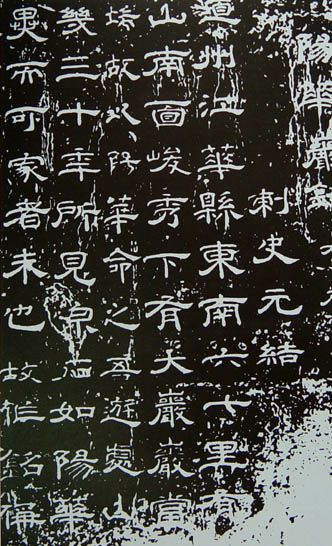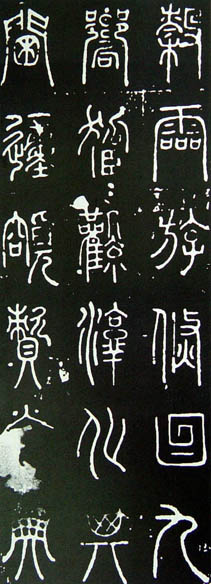
瞿令问简介
一作令闻,生平无考,或以为望出博陵(今河南蠡县),唐代宗时人。历道州江华县令,为元结道州刺史下属。工书,尤工杂体篆及八分。与元结友善,时元结为道州刺史,作文辄与瞿书之。元结曾为峿台(在湖南祁阳,767年刻石,未署书者)、浯溪、寒亭三铭,后二铭皆为瞿篆书。元结《阳华岩铭》即有“县大夫瞿令问,艺兼篆籀”。另瞿篆书《窳尊铭》(766年刻石道州),“《窳尊铭》结体遒劲,见称于清瞿中溶,并认为在袁滋之上,其《古泉山馆金石文编》曰:“所用古文,皆有依据,无一字杜撰,以次见公篆学之精深,实于唐宋诸儒中卓然可称者”。朱关田《中国书法史.隋唐五代卷》中亦称“有唐一代悬针之篆,当推瞿氏为第一”。
瞿令问《阳华岩铭》(局部) 高76cm 宽276cm 766年
《阳华岩铭》,唐永泰二年(766年)刻,在湖南江华县(今江华瑶族自治区),元结撰文,瞿令问书,刻于摩崖。前七行序文为隶体,后三十五行铭文,仿魏三体石经体例,每字先古文,次小篆,再次隶书。